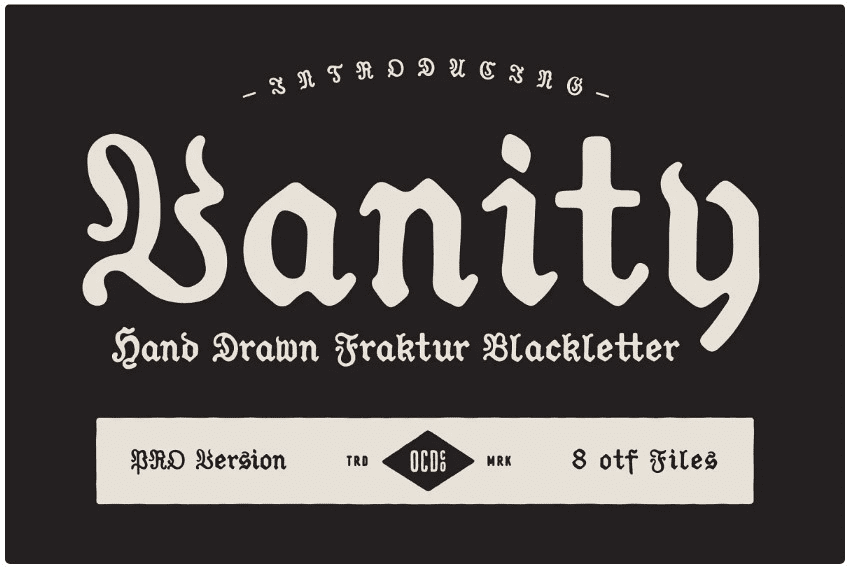
[Creativemarket] Vanity Font
Название: Vanity Font
[Creativemarket] Vanity Font
Тщеславие - это классический стиль Fraktur Blackletter, который тщательно нарисован вручную и адаптирован для лучшей читаемости на английском языке. Тщеславие поставляется в 8 тщательно обработанных стилях, а также с выбором лигатур. Дайте вашей работе неоспоримое качество ручной работы с этим крутым и уникальным семейством Blackletter.